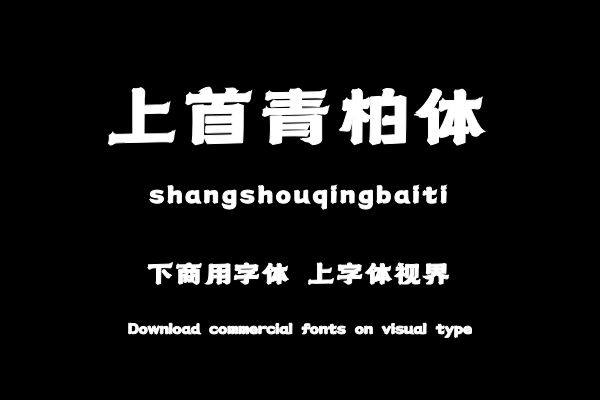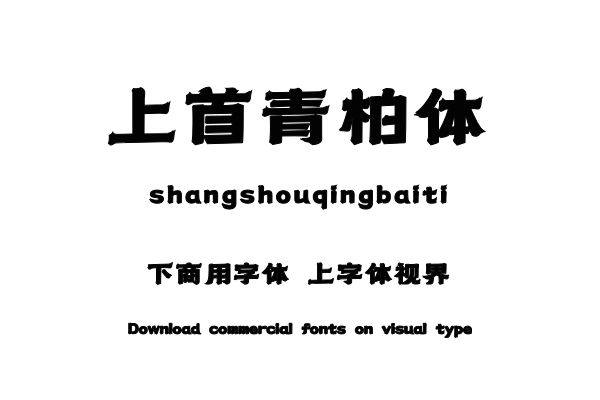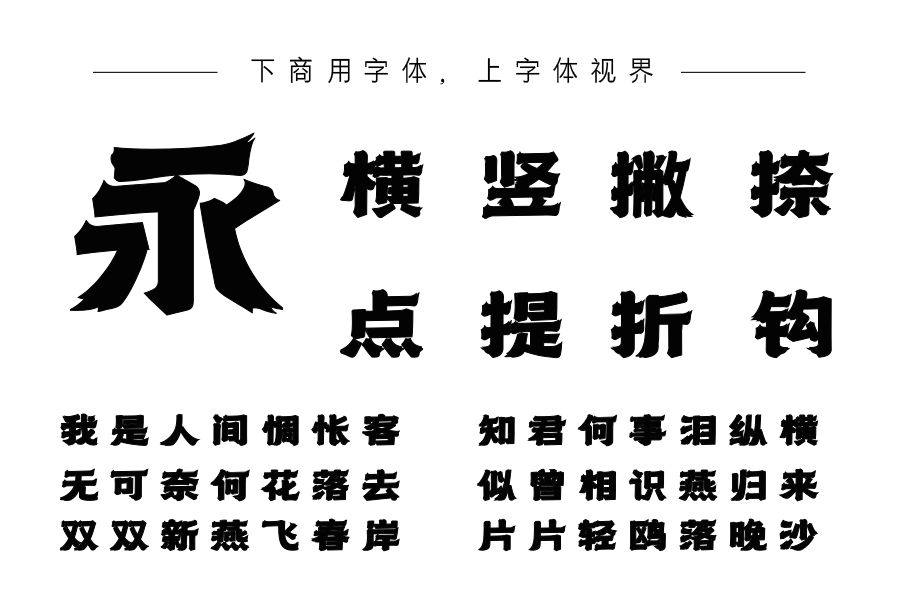
上首青柏体字体整体以黑体为框架,将一些原始的元素融合进字体,而字体笔画粗细均匀,整体方正有力,使字体在拥有原始野性力量的同时又不失现代字体的简洁大方。字体整体符......购买须知:“下载服务费”与“字体VIP”所获得字体 仅用于个人非商用, 商用请联系付费授权。本字体为电脑用字,手机没有root权限不支持直接手机换字(手机如何root,请自行百度搜索教程)。购买前请先 了解清楚后再付款 ,字体为虚拟产品无法回收 一旦购买不支持退款。